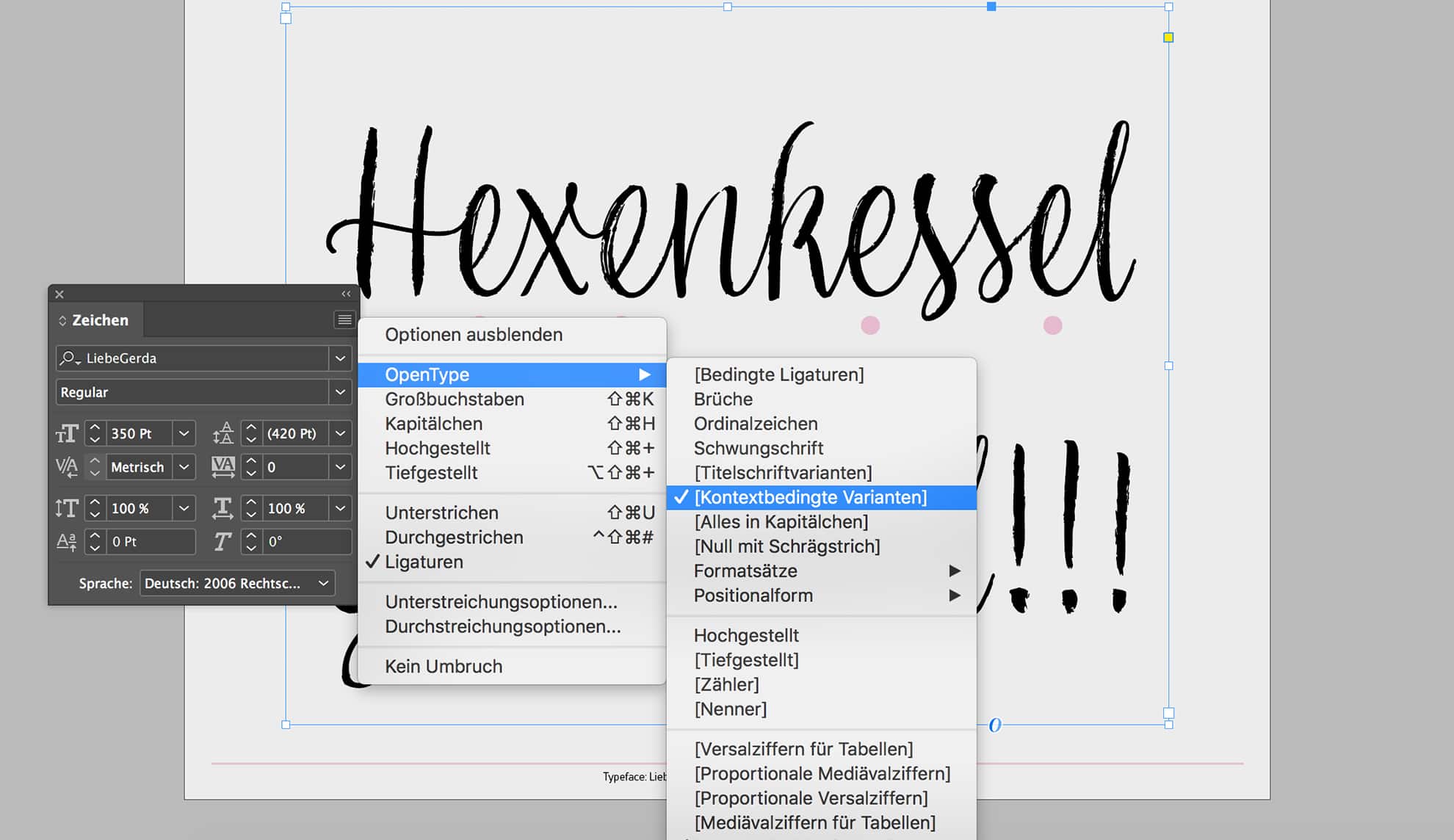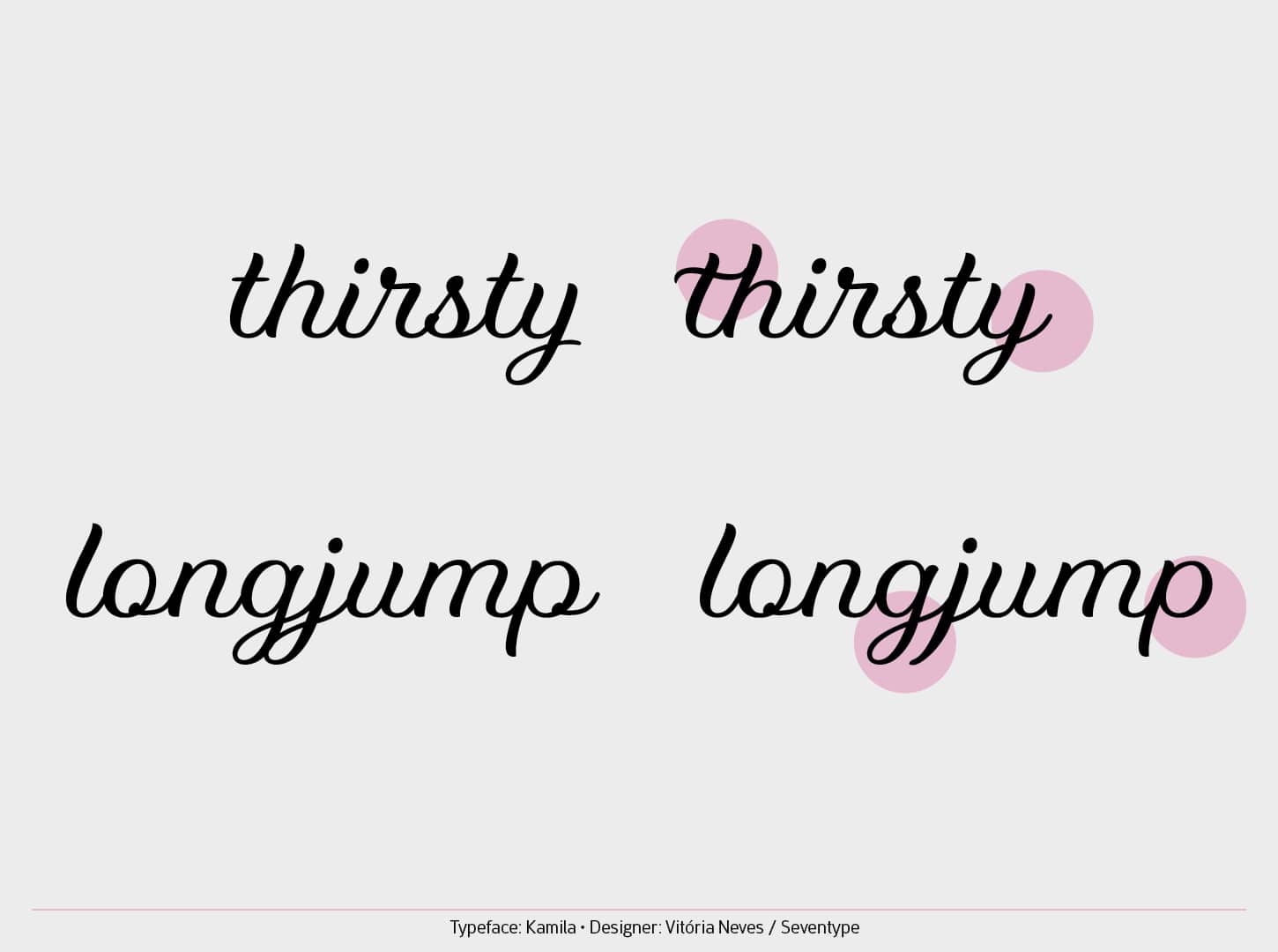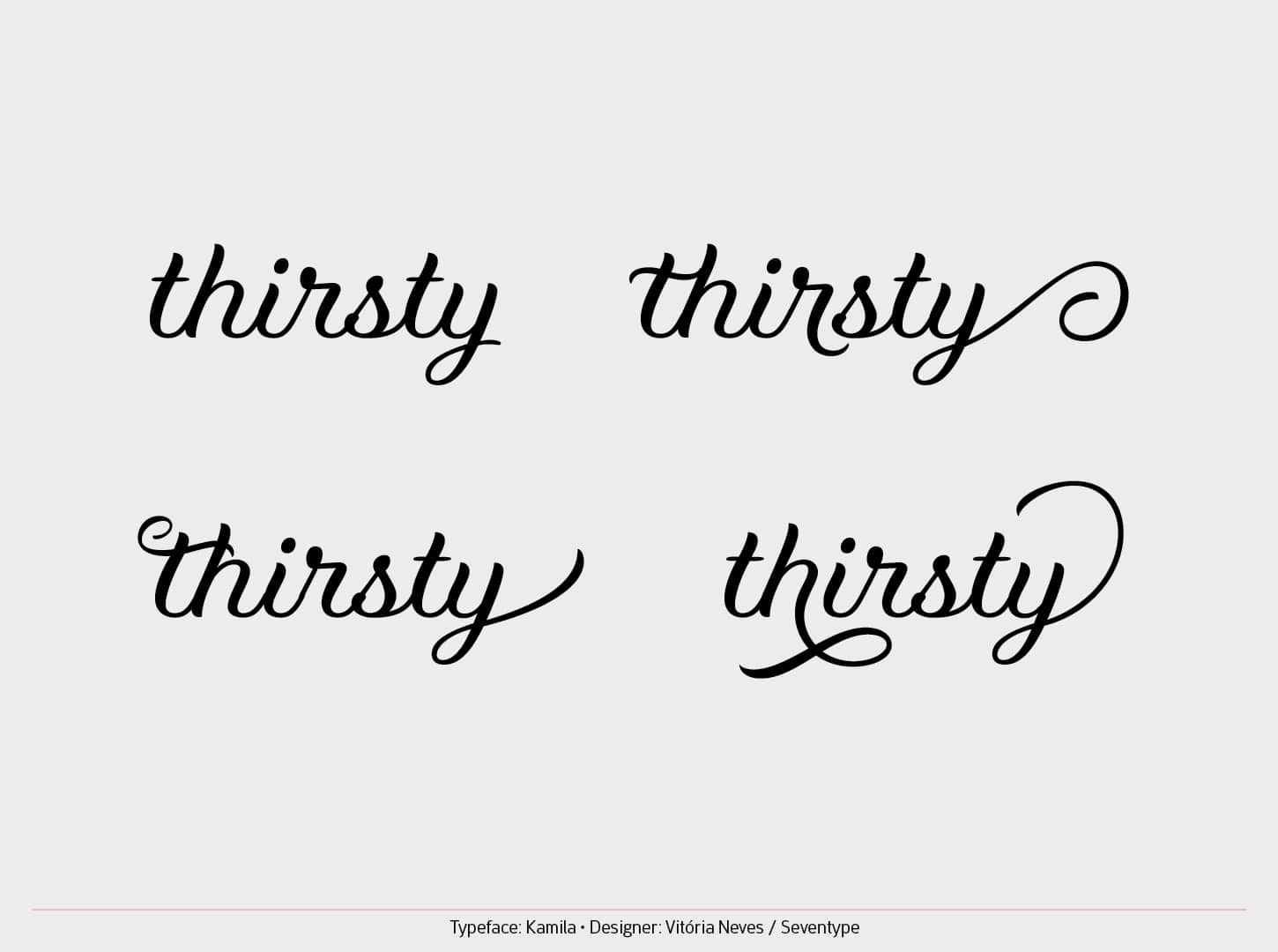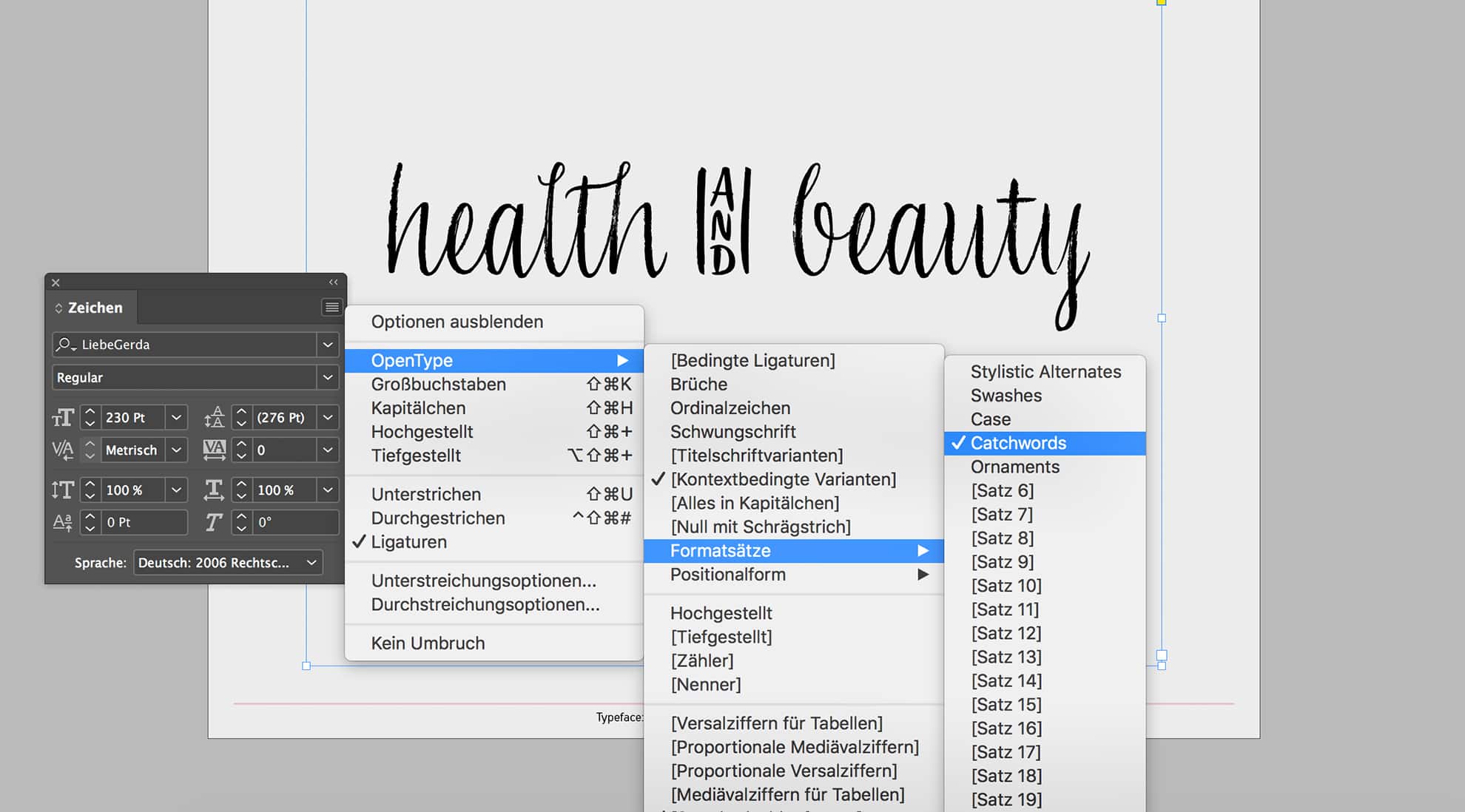
Im ersten Teil wurden erste Einblicke in die Welt von Open Type Features gegeben und gezeigt, wie man diese findet und aktiviert. Die verschiedenen Einsatzmöglichkeiten der dabei angesprochenen alternativen Zeichen sind breit gefächert. Doch sind diese Alternativen wirklich nötig? Und worin besteht eigentlich deren Mehrwert? Alternative Buchstaben lassen sich insbesondere bei gut gestalteten Script-Fonts finden, welche einer Handschrift nachempfunden werden.
Script-Fonts genießen insbesondere in der Lebensmittel- und Kosmetikindustrie sehr große Beliebtheit, seitdem sich das Konsumverhalten der Gesellschaft mehr und mehr zu bewussten, nachhaltigen und auch selbstgemachten Produkten hin bewegt. Nimmt man zum Beispiel einen Rundgang durch den Discounter unseres Vertrauens, springen uns die Marken- und Produktnamen in geschwungenen Formen praktisch entgegen. Die Werbebotschaft hierbei ist klar. Aber auch Influencer, Modelabels und DIY-Designer greifen gerne zu Script-Fonts um eine persönliche Note mit einfliessen zu lassen. Persönlichkeit, Individualität, Qualität und Nachhaltigkeit sind einige der maßgeblichen Eigenschaften, die einen Script-Font für die Markenkommunikation interessant machen.
Contextual Alternates
Doch was unterscheidet einen guten von einem schlechten Script-Font? Sich wiederholende identische Zeichen, oder wahllos springende Zeichen sind unschön und wirken sehr technisch und konstruiert. Denn, auch wenn man kalligrafisch noch so begabt und trainiert ist, man wird es wohl kaum hinbekommen zwei komplett identische Buchstaben nebeneinander zu zeichnen. Und genau darum benötigt man alternative Buchstaben. Denn gerade durch diese Unregelmäßigkeiten erreicht man, dass ein Schriftzug wirklich handgeschrieben und natürlich wirkt, und eben nicht konstruiert. Dank der „contextual alternates“ können gut gestaltete Schriften, wie zum Beispiel „LiebeGerda“ von Ulrike Rausch, alternative Buchstaben automatisch darstellen, wie im Beispiel „Hexenkessel“ mit den unterschiedlichen „e“ oder beim Werbewort „Goooaaal!!!“ zu sehen. Gleiche Buchstaben sind unterschiedlich gezeichnet und wirken dadurch wirklich handgemacht. Sogar zu den Ausrufezeichen gibt es Alternativen.
Bei perfekt gestalteten und programmierten Schriften, wie dieser, erscheinen die alternativen Zeichen automatisch beim Schreiben. Sollten sie zum Beispiel in Adobe InDesign nicht gleich zu sehen sein, kann man diese in den Open Type Features unter „Kontextbedingte Varianten“ aktivieren. Alternativ kann man unter anderem auch beim Markieren eines einzelnen Buchstaben Varianten selbst bestimmen, wie im ersten Teil bereits ausführlich beschrieben.
Ligaturen
Script-Fonts, bei denen die Buchstaben wie in Schreibschriften flüssig ineinander übergehen, benötigen neben den alternativen Zeichen auch alternative Übergänge und Ligaturen. So weist zum Beispiel „Kamila“ von Vitória Neves unzählige Varianten an Ligaturen auf. Das „th“ im Wort „thirsty“ erhält zum Beispiel eine individuelle Kombination, um natürlicher und schwungvoller zu erscheinen, als die individuellen Zeichen „t“ und „h“ nebeneinander. Auch das „gj“ im Wort „longjump“ kollidiert in der Kombination der Einzelzeichen, was durch eine Ligatur behoben werden kann. Das „y“ und „p“ am Ende der beiden Worte bekommt durch „contextual alternates“ eine alternative Endung, die einem natürlichen Abschluss eines geschriebenen Wortes gleicht.
Stylistic Alternates, Swashes, Catchwords & co.
Ein Script-Font kann einfach nicht genug alternative Zeichen haben. Allein Kamila kann zum Beispiel unzählige Variationen des Wortes „thirsty“ darstellen. Durch stilistische Alternativen und Swashes können einzelne Zeichnen ausgetauscht, und somit das Gesamtbild völlig verändert werden. Und das alles mit ein und demselben Font.
Auch Catchwords sind ein tolles Feature um einen Lettering-Stil mit einfliessen zu lassen, ohne das Textwerkzeug zu verlassen. Am Beispiel „health and beauty“, gesetzt in LiebeGerda, wunderbar zu sehen. Desweiteren können viele weitere Features eingesetzt werden, um einen handgeschriebenen und individuellen Charakter zu erhalten. Und wenn sie, wie hier zu sehen, in den Open Type Features eindeutig beschrieben sind, findet man sie auch ganz leicht.
Fazit – Woran erkennt man also gute Script-Fonts?
Ein Script-Font ist erst dann gut, wenn er nicht wie ein Font wirkt. Eine umfangreiche Auswahl an alternativen Zeichen und Features ist also unverzichtbar, wenn man einen natürlichen, handgeschriebenen Text darstellen möchte. Zu empfehlen ist daher, schon bei der Recherche in die Glyphenpalette und Open Type Features zu schauen. Denn erst mit einem richtig guten Script-Font macht es auch richtig viel Spaß mit Schrift zu spielen.